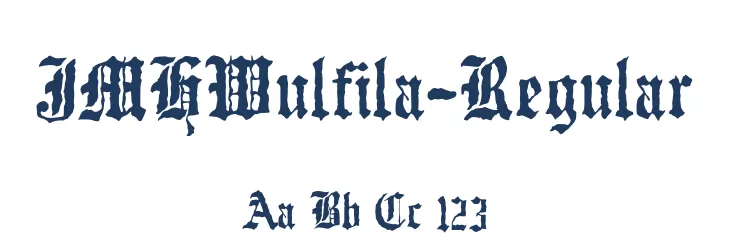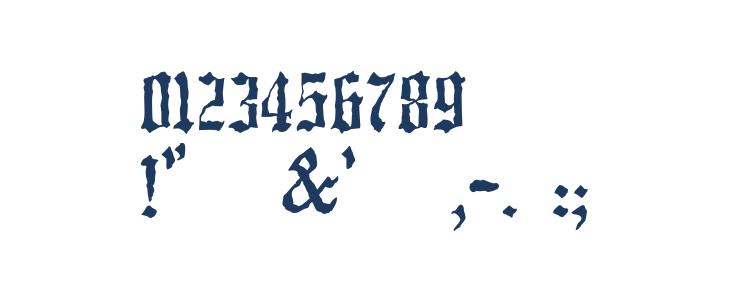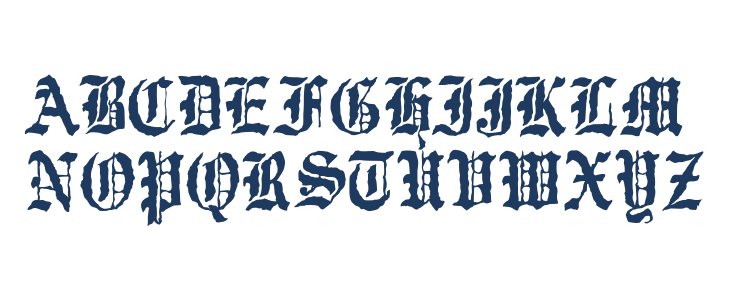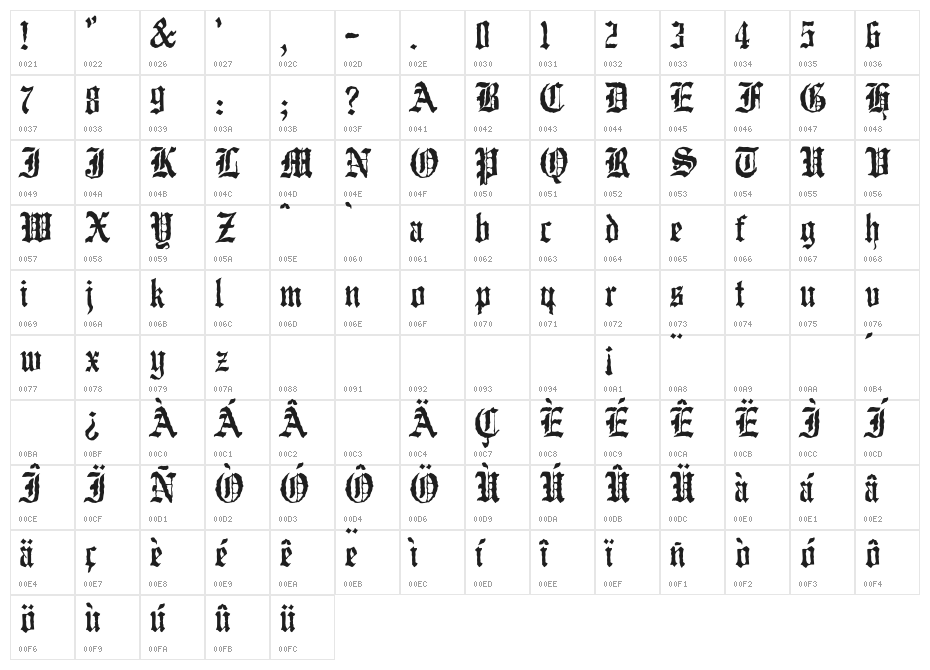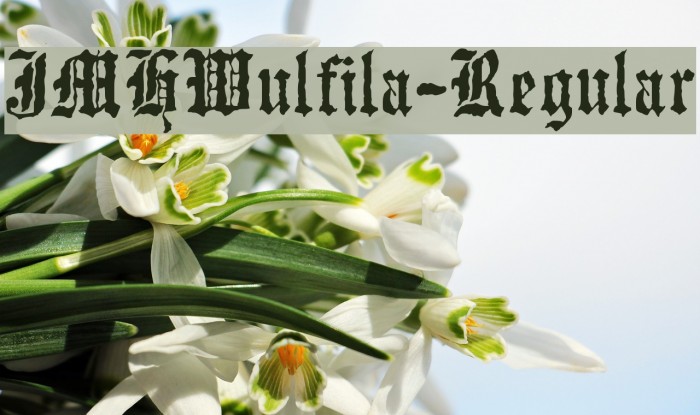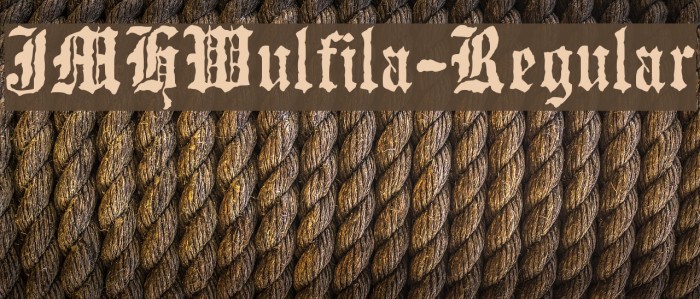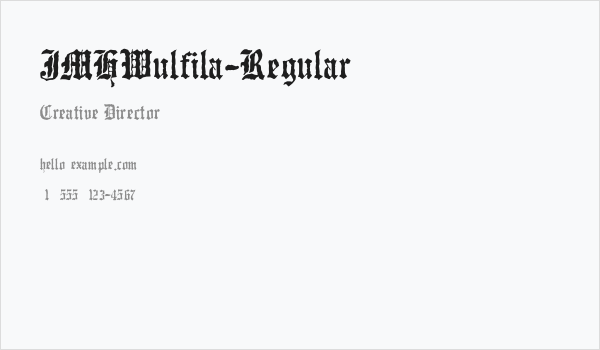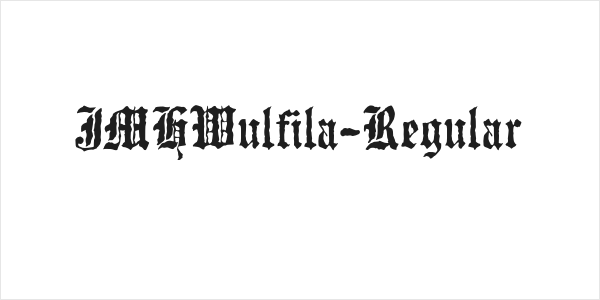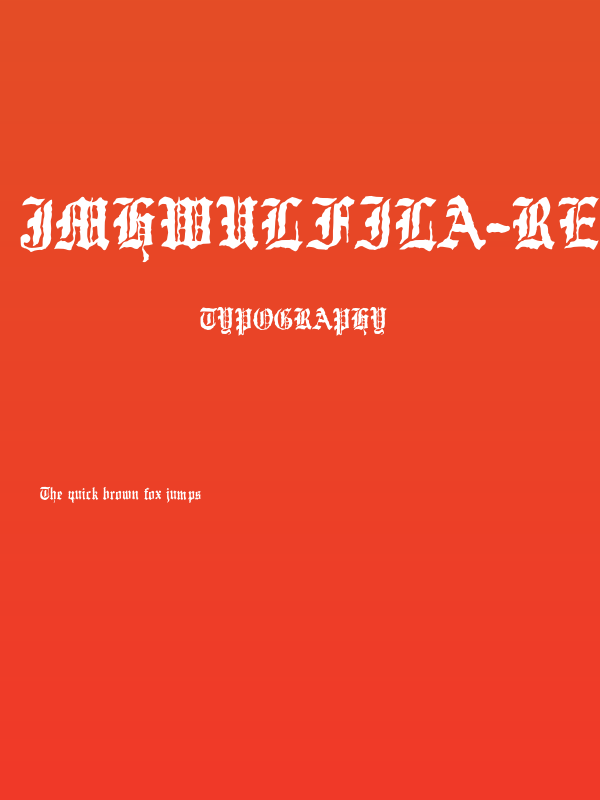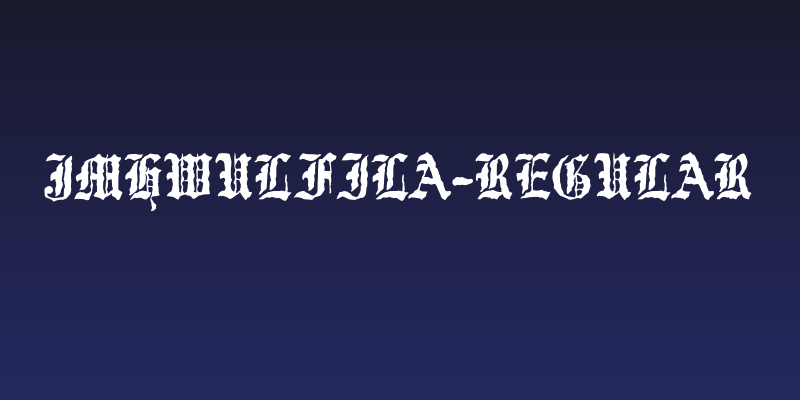
JMHWulfila-Regular Font
| 整体风格 | Vintage |
| 使用场景 | Logos, Headlines, Decorative text |
| 推荐项目 | Ideal for historical documents, vintage posters, book covers, and branding that requires a gothic or medieval theme. |